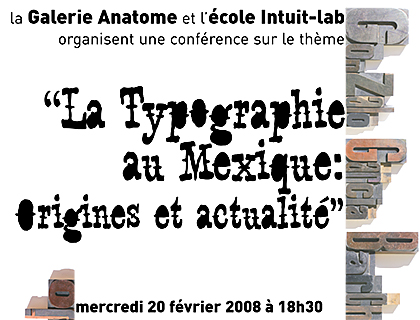
La typographie au Mexique | à la Galerie Anatome
Mercredi
20 février 2008
à 18h30
à la Galerie Anatome
Cette conférence a pour but de montrer l’état actuel des Arts et Métiers typographiques au Mexique a partir d’une révision des styles graphiques pré et post-hispaniques dans cette région.